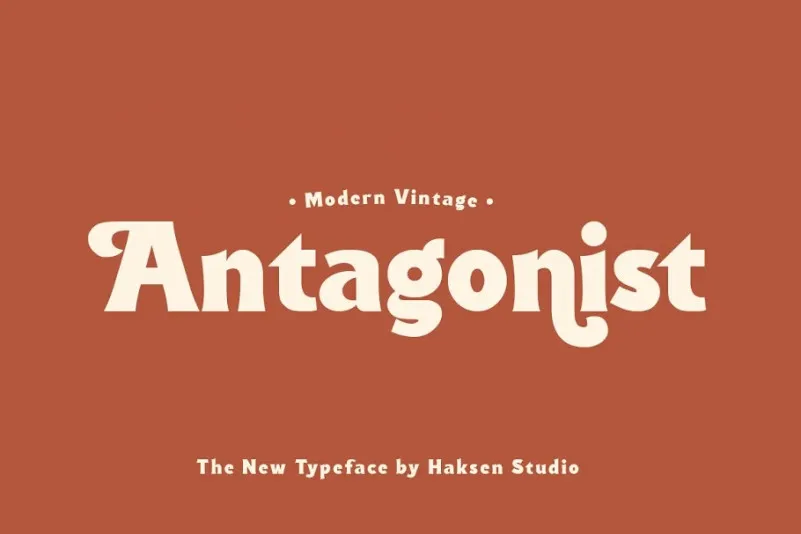
Antagonist Bold Serif Font – Download Grátis
A Antagonist Bold Serif Font é uma criação singular, divertida e versátil que traz à tona a elegância dos serifos no formato bold. Desenvolvida por Haksen, esta fonte oferece um equilíbrio perfeito entre as letras maiúsculas e minúsculas, proporcionando um estilo agradável em ambientes tanto formais quanto informais. Suas alternativas para letras maiúsculas e minúsculas permitem uma gama ampla de opções de design, tornando-a ideal para diversos usos, como headlines, logos, postais, embalagens, camisetas de campanha ou até mesmo cartazes. Seu rico vocabulário em serifas permite que você realize inúmeras combinações e criações únicas, tornando esta fonte uma escolha perfeita para impulsionar seu design de qualquer modo que você possa imaginar.